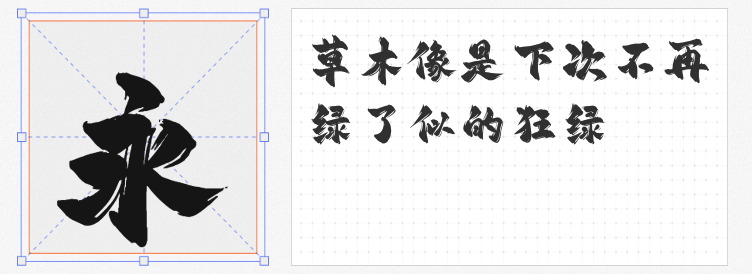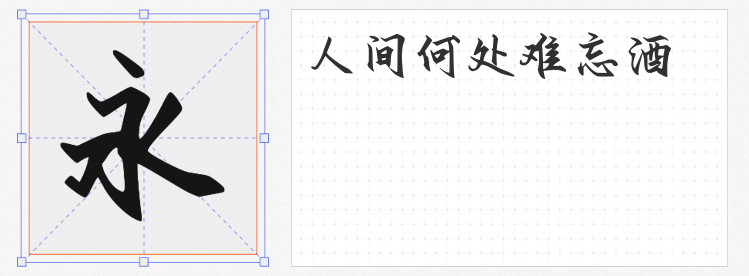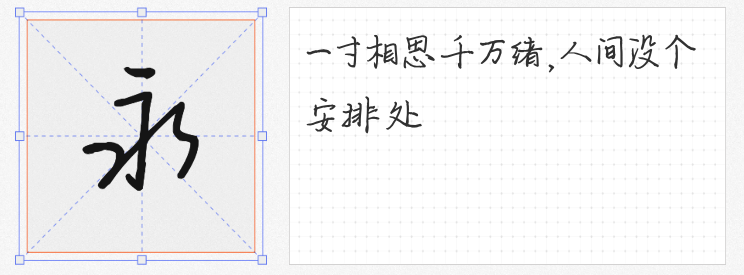
建军节主题设计需兼顾庄重感与视觉冲击力,手写字体的运用能巧妙平衡工整结构与艺术张力。以下四款免费商用字体各具特色,均通过权威平台授权验证,可放心应用于海报、展板、宣传册等场景。
由字体家AI神笔造字生成的这款字体,以法律从业者的严谨笔触重塑手写温度。笔画粗细均匀,结构端庄如楷书,却因自然连笔保留了书写痕迹的灵动感。例如在"八一军魂"主题海报中,该字体能清晰呈现标语内容,同时通过微妙的笔画弧度传递人文关怀。
这款以"飞扬"命名的书法字体,通过浓墨飞白效果再现毛笔挥洒的力度感。超粗笔触与枯笔纹理形成强烈视觉对比,特别适合表现"铁血军魂""战无不胜"等主题。在红色背景的建军节展板中,该字体可与烫金工艺结合,营造出"笔下山河图,豪情万丈"的意境。
融合黑体结构与卡通元素的创新设计,打破传统军旅题材的严肃感。方正规整的笔画框架中,圆角处理与适度倾斜赋予字体活泼气质。例如在"青春献军营"征兵宣传中,该字体既能保证信息可读性,又能通过俏皮细节吸引年轻群体关注。
以硬笔书写特性重构书法美学,纤细线条中蕴含行云流水的韵律感。特别适合长标题排版,如"光荣与使命——庆祝中国人民解放军建军98周年"等复合型文案。在浅灰色底纹上使用该字体,既能保持版面整洁,又能通过笔触粗细变化突出关键词。
这四款字体既延续了传统书法的精神内核,又通过现代设计语言焕发新生,完美契合建军节设计所需的"工整气势"与"艺术张力"。设计师可根据具体场景需求,灵活组合运用以创造视觉层次。